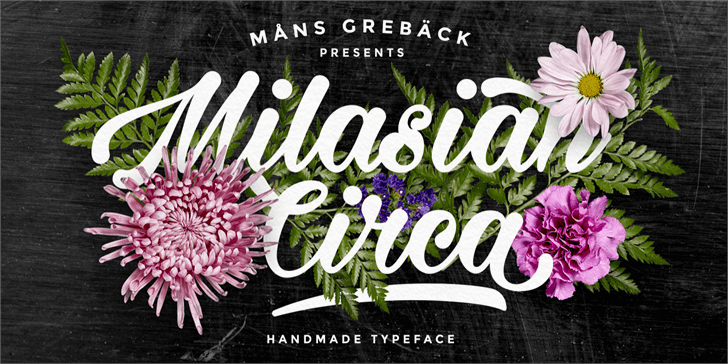
Milasian Circa Bold font – Download Grátis
A Milasian Circa Bold é uma fonte original criada por Måns Grebäck em 2015. Esta elegante escolha para seu próximo projeto de design escrita a mão foi projetada para dar um toque pessoal e autêntico às suas criações digitais. Seu estilo casual mas profundo encaixa-se perfeitamente tanto em fontes serifadas quanto naquelas sem traços, permitindo que você personalize sua página ou projeto de forma única e expressiva. Esta fonte foi desenvolvida especialmente para aqueles que valorizam um toque autêntico e pessoal em seus trabalhos digitais. Ela é perfeita para quem procura uma maneira criativa de personalizar seu design, seja ele escrito a mão ou digitalizado. A Milasian Circa Bold oferece uma combinação única de delicadeza e força, proporcionando um resultado profissional sem perder o aspecto natural da escrita humana. A Milasian Circa é mais do que apenas outra fonte; ela é uma maneira para você expressar sua personalidade de forma elegante e eficaz. Seja em anúncios, websites ou qualquer outro projeto digital, a Milasian Circa Bold certamente se encaixa perfeitamente na sua paleta de recursos gráficos.